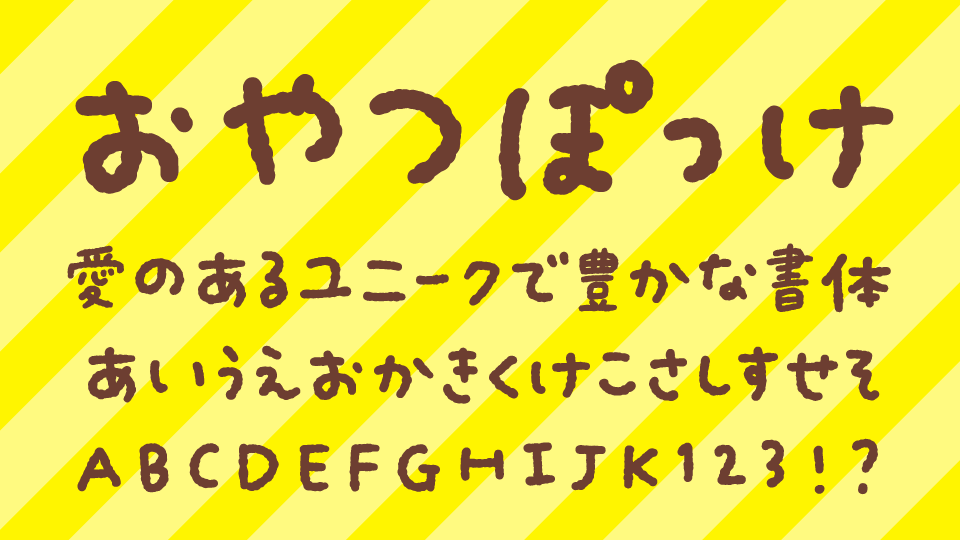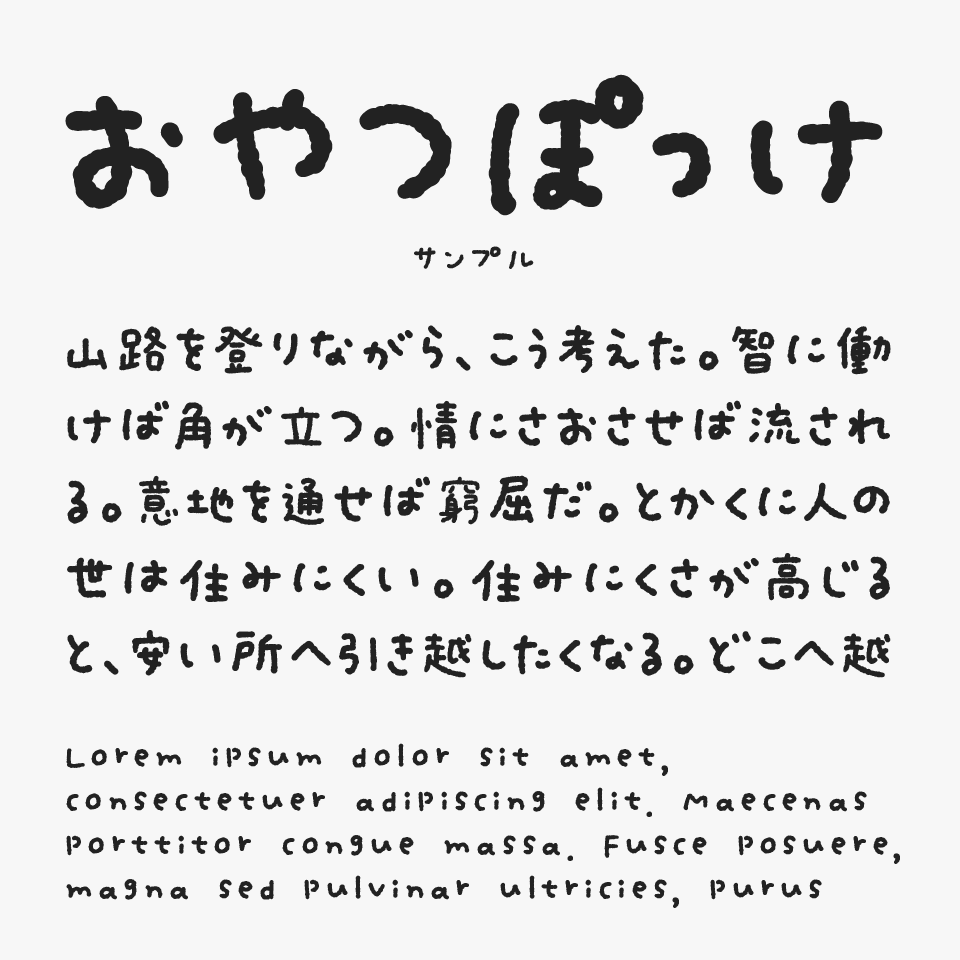
おやつぽっけ
おやつぽっけフォントは、ふっくらと丸みのある文字に、少し凸凹とした輪郭を組み合わせた、やさしく可愛らしい手書きフォントです。
手作りのお菓子のような温もりがあり、眺めているだけでほっとするような柔らかな雰囲気が感じられる手書き文字です。太めのシルエットで読みやすく、小さなサイズでも可愛らしさがしっかり伝わるのも魅力です。
お菓子のパッケージやカフェメニュー、絵本、子ども向けコンテンツ、ハンドメイド作品、イベントPOPなど、温かみを大切にしたデザインにぴったりなフォントです。ナチュラルで親しみやすい雰囲気を加えたいときにも使いやすいフォントです。
愛知県で洋菓子店を営む作者が制作しており、お菓子づくりを思わせるやさしい世界観が、フォントにも自然と息づいている可愛らしいフォントに仕上がっています。